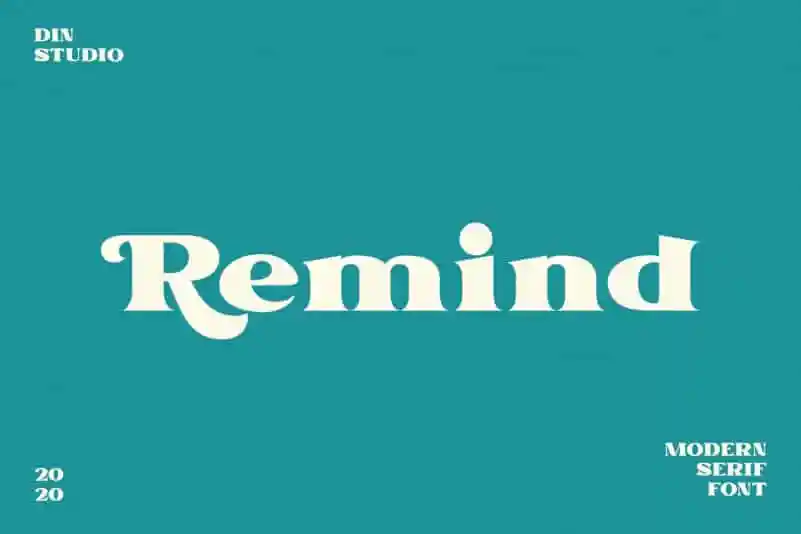
Remind Serif Font – Download Grátis
Remind Serif é uma elegante fonte geométrica do tipo serif que se destaca por sua legibilidade e beleza sofisticada. Com suas partes arredondadas e curvas suaves, remete aos caracteres de uma tipografia mais tradicional, mas incorpora elementos geometricamente perfeitos para um toque moderno. Esta fonte é ideal para trabalhos profissionais que valorizam estética e qualidade, proporcionando ao seu design uma beleza atraente e inspiradora. Em um mundo cada vez mais digitalizado, Remind Serif oferece uma conexão visual com o passado do tipo de letra enquanto se destaca com sua simplicidade geométrica e elegância moderna.